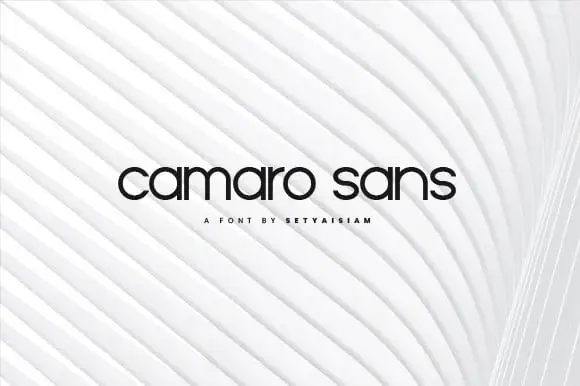
Camaro Sans Serif Font – Download Grátis
A Camaro Sans Serif Font é uma opção atraente para designers que desejam dar vida aos seus projetos digitais com estilo moderno e elegante. Desenvolvida pelo designer setyaisiam, ela captura a essência de um tipo sério e sofisticado, capaz de transitar fluidamente entre texturas finas e exuberantes para uma experiência visual única. Esta fonte traz à tona uma mistura irresistível de modernidade e nostalgia, proporcionando aos criativos uma ferramenta versátil que pode ser usada tanto em interfaces digitais modernas quanto em projetos impressos ou digitais do futuro. Com seu estilo clássico aparentemente atemporal, a Camaro também traz consigo um toque amigável e descontraído, tornando-a uma escolha ótima para qualquer projeto de design que exija uma presença visual moderna e persuasiva. O designer setyaisiam soube capturar essa harmonia perfeita entre versatilidade e elegância na Camaro, permitindo a ela ser um aliado valioso tanto nas telas quanto nos papéis impressos.